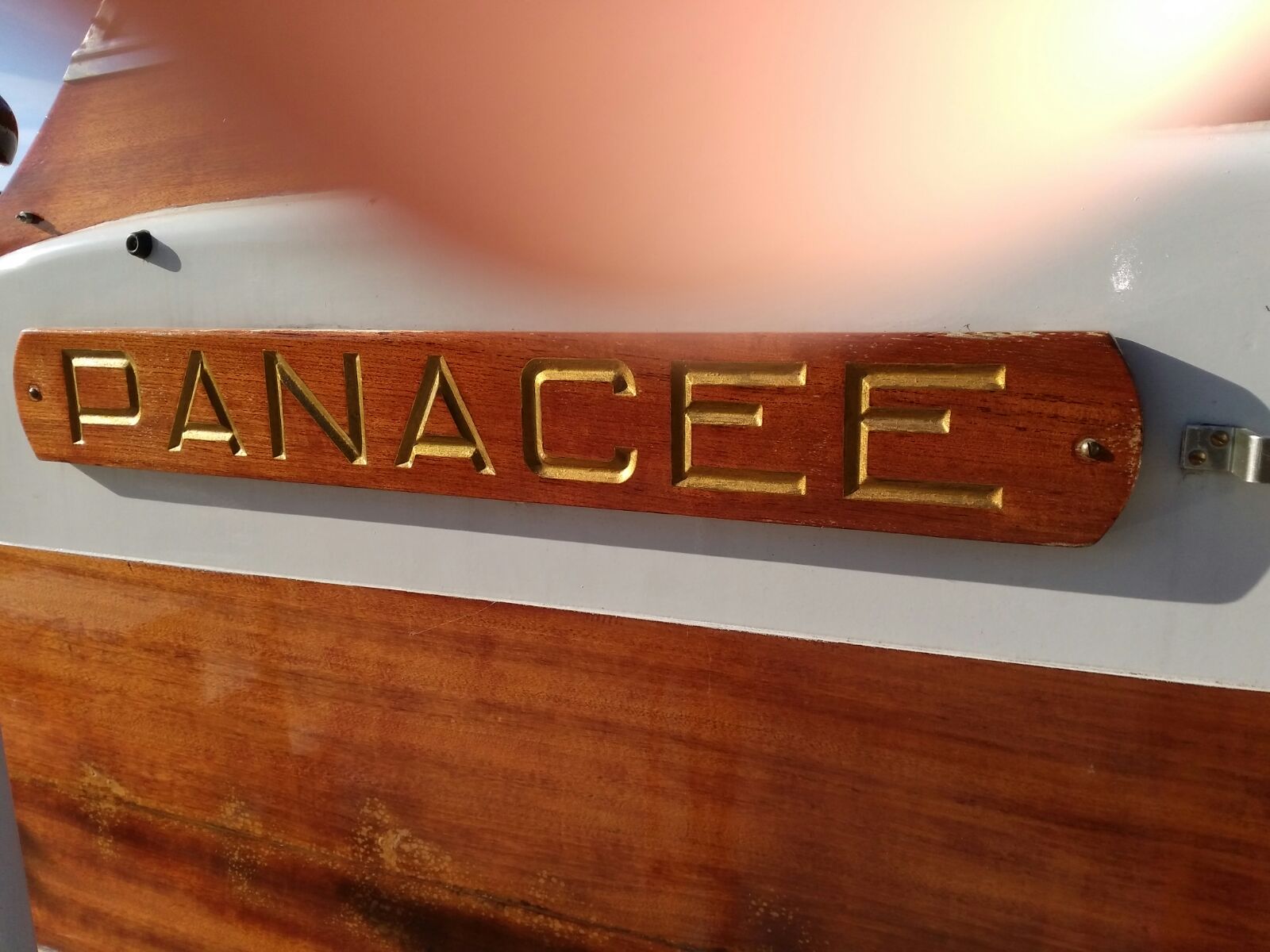
Schrift einer in Holz gefrästen Bootsbeschriftung gesucht.
Weitere Angaben hab ich leider nicht.
Gab es für solcherlei Beschriftungen Maschinen, die z.B. die Form von Schablonen abgenommen und ins Holz gefräst haben? Heute würde das ja CN-gesteuert ablaufen …
Kopierfräsen können dies. Allerdings sind die Strichenden (dreieckige Facetten) so nicht fräsbar, da die Fräswerkzeuge und ergo die gefräste Form rotationssymmetrisch sind.
Bei einem Einzelstück wie dem Bootsnamen kann ich mir auch eher Handarbeit vorstellen – die Frage nach der Maschine war mehr allgemeiner Art.
So etwas lässt sich sehr wohl Kopierfräsen, die scharfen Kanten in den Linienenden entstehen, wenn der keglige Fräser dort in den 45° Kanten hoch gezogen wird.
Dass sich so etwas auch mit einer Fräse herstellen läßt, mag schon sein. Das Problem ist aber, dass die Fräse, auch wenn sie noch so genau arbeitet, das Holz aufrauht. Hingegen der Schnitt schlicht und einfach materialgerecht ist und die Fasern glatt abschneidet.
Ein geübter Hanwerker, der den Kerbschnitt beherrscht, macht so etwas auch schneller und weniger umständlich, als mit einer Fräse.
Es gibt sicher noch viele Möglichkeiten und Techniken, die zum Ziel führen, aber dem gezeigten Beispiel wird m. E. der Kerbschnitt am gerechtesten.
Das trifft auf die Flanken zu.
Die Spitze der V-Form am Ende der Flanken kann aber mit der Fräse nicht in der gezeigten Art entstehen.
Eben doch, wenn der unten spitz zulaufende Fräser in eben dem Grund der V-förmigen Flanke hoch gezogen wird, also entsprechend dem Grund der Buchstaben, aber dann eben schräg nach oben hin.
Das wäre dann ein Fräser mit einer Spitze.
Längsgefasertes Holz, wie in diesem Fall, wird nicht mit einem spitzförmig zulaufenden Fräser gefräst. Man würde, wenn überhaupt,  damit kein gutes Ergebnis erzielen.
Spitzförmige Fräser wurden bei Hirnholz verwendet, z. B. bei Holzstichen des 19. Jh.
Aber wie gesagt, irgendwie geht natürlich alles. Und wie oben erwähnt, es gibt viele Methoden um zu einem Ergebnis zu gelangen.